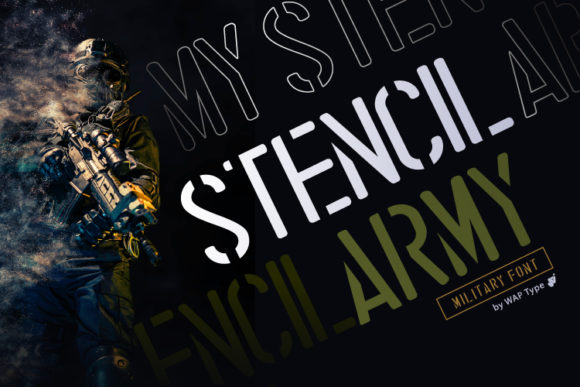
Stencil Army - это уникальный шрифт с военным стилем.
Этот шрифт был создан для серии плакатов, посвященных ветеранам, но вы также можете использовать его в любом другом проекте.